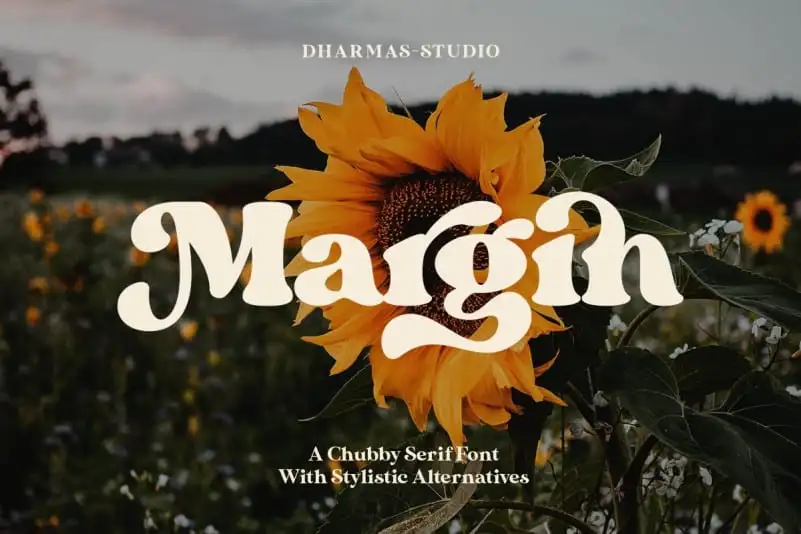
Margin Serif Font – Fonte Grátis
Margin Serif Font
A Margin Serif Font é uma nova tipografia serif que lembra os anos 70 de forma vintage. Com uma forma poderosa e elegante, essa fonte oferece uma opção atraente para textos multilíngues. Seu design único se destaca em especial com uma alternativa rica em detalhes e um traço muito forte que dá ao texto um toque intrigante. Esta fonte é altamente versátil, ideal tanto para aplicações comerciais quanto editoriais, tornando-a uma escolha inteligente para designers gráficos. Se você está procurando por uma fonte serif que traz a nostalgia dos anos 70 à sua próxima criação de design, Margin Serif pode ser exatamente o que você precisa.